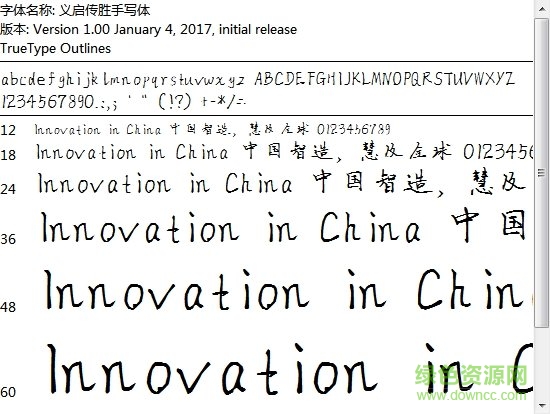
義啟傳勝體是一款不同于義啟手寫體的義啟字體,筆觸有力而沉重,給人端正沉穩(wěn)的視覺魅力,讓你的藝術(shù)設(shè)計更增獨特魅力,綠色資源網(wǎng)誠意推薦!
義啟傳勝字體瀟灑落拓,給人干凈清爽的視覺呈現(xiàn),讓文字蒼勁有力度,是一款行筆流暢的硬筆書法字體,效果十分出眾。
義啟傳勝體與義啟手寫字體比較接近,但義啟傳勝體更顯筆畫端正,英文字母有著更為圓潤的形態(tài),可以廣泛使用在手寫作品的文字裝飾中。